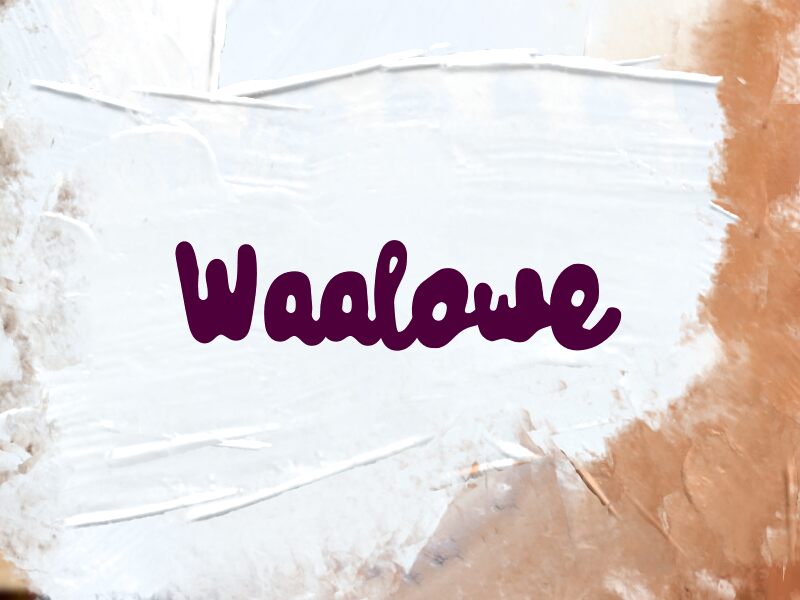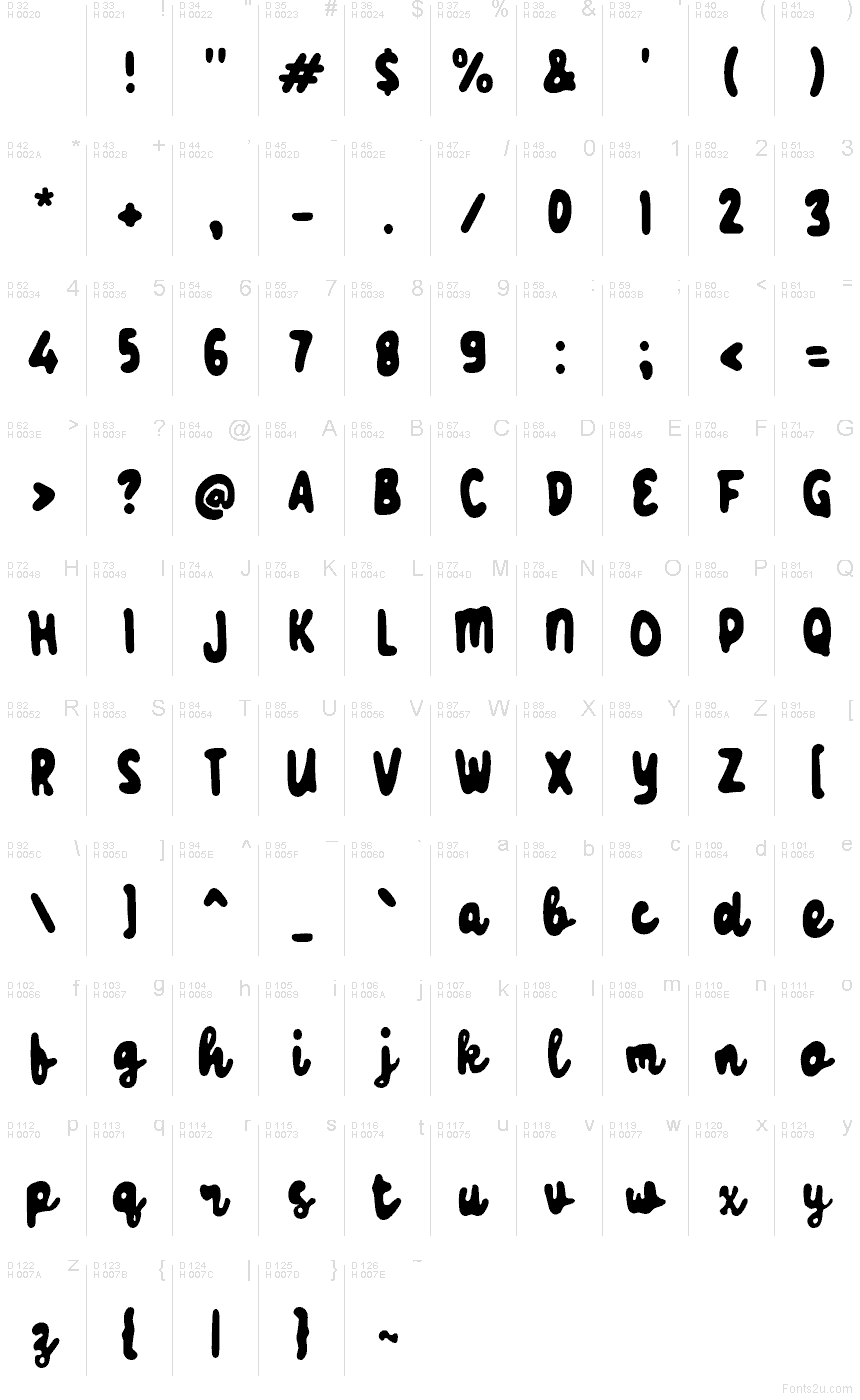
Waalowe
Waalowe od Wep je bezplatné písmo typu brush definované zaoblenými tvarmi, ktoré pôsobia skôr ako jemné kvapky atramentu než ako rýchle ťahy štetcom. Vďaka hravému rytmu a detailom v tvare slzy má toto písmo rukodielny a jemne gélový charakter, ktorý si zachováva skvelú súdržnosť v celej sade.
Tieto plné tvary sa skvele hodia na nálepky, neformálne logá, detské obaly, príspevky na sociálne siete alebo krátke nadpisy na plagáty, kde dizajnu dodajú fluidný a organický vzhľad. Písmo sa tiež hodí na hravý merch a úvodné titulky, najmä ak hľadáte vzhľad, ktorý pôsobí osobne a hmatateľne, nie príliš strojene alebo vzdušne.